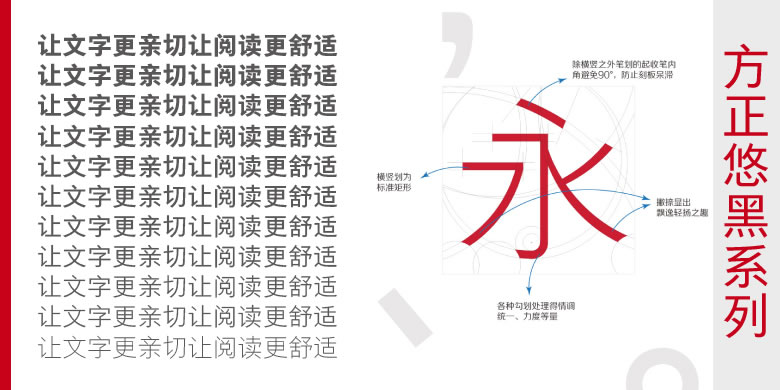
方正悠黑_GBK-503L方正悠黑系列
品牌:方正字库设计师:仇寅发行时间:2014字库编码:大陆简体(GB2312-80)、简繁扩展(GBK)、大陆繁体(GB12345-90)分类:黑体
方正悠黑_GBK-503L方正悠黑系列
方正悠黑家族是方正第二代中文屏显字体。其设计充分利用高清屏幕的物理特性,寻求新技术和传统审美之间的平衡;适当收紧中宫和缩小字面,使得单字的轮廓清晰,易于阅读识别。笔形保留了汉字书写的笔锋特征和间架结构,适合长时间屏幕阅读。方正悠黑家族由135款字体组成,包括15种字重,4种扁字形和4种长字形。此外,还专门设计了全套的西文字体和符号,使不同字重的西文字体在与中文混排时更加协调一致。方正悠黑的设计富含人文气息,排版清朗温润,不但适用于各种便携式屏幕,还适用于传统印刷媒介。